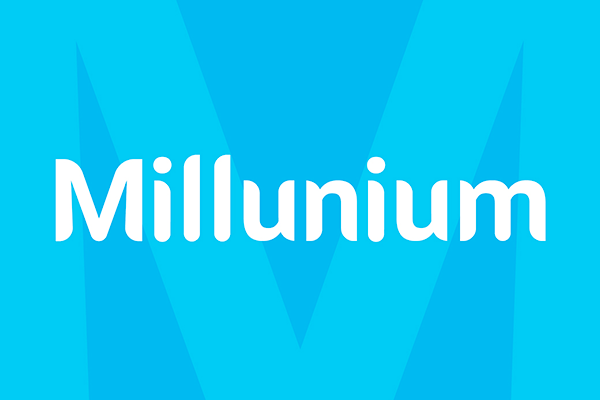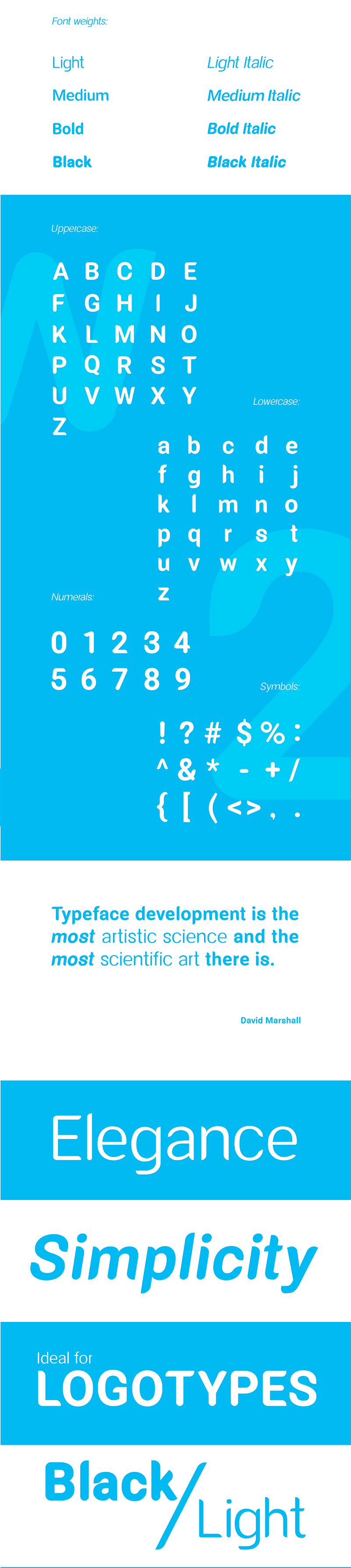
Millunium是一款由国外设计师Kolcsár Sz. Zsolt创作的优雅且圆润的免费英文字体。
Kolcsár Sz. Zsolt在Behance上首次发布了Millunium字体,并明确表示该字体可用于个人和商业用途,无需付费。Millunium字体的优雅和圆润特性使其成为从徽标到海报,从品牌到标题等各种设计项目的理想选择。